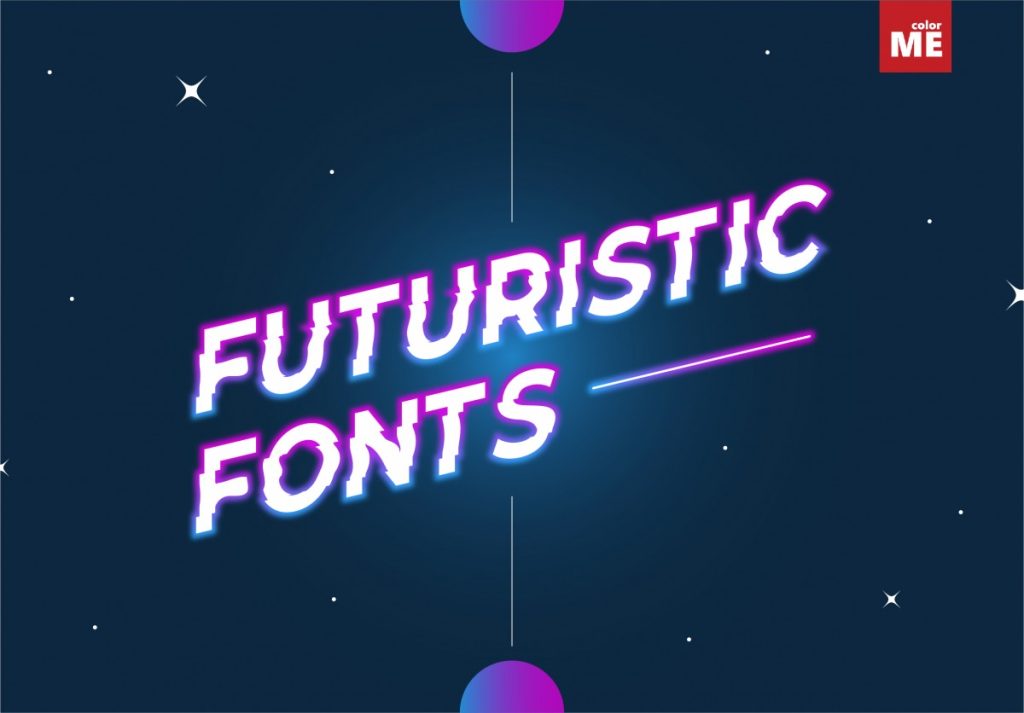
Font Futuristic Việt Hóa
Bộ Font: Futuristic
Font Futuristic Việt Hóa là phiên bản Việt hóa của các phông chữ mang phong cách tương lai, với thiết kế độc đáo, hiện đại và sáng tạo. Font Futuristic Việt Hoá là một font chữ thuộc bộ font chữ Việt Hoá  thường có các đường nét góc cạnh, phá cách và mang lại cảm giác công nghệ cao, lý tưởng cho các dự án liên quan đến chủ đề khoa học viễn tưởng, công nghệ, hoặc các thiết kế mang tính tiên phong. Với khả năng hỗ trợ đầy đủ ký tự tiếng Việt, Font Futuristic Việt Hóa giúp bạn dễ dàng áp dụng vào các thiết kế nội địa mà vẫn giữ được sự mới mẻ và hiện đại. Đây là lựa chọn hoàn hảo cho những ai muốn tạo ra các tác phẩm nổi bật, đậm chất tương lai và thu hút sự chú ý.